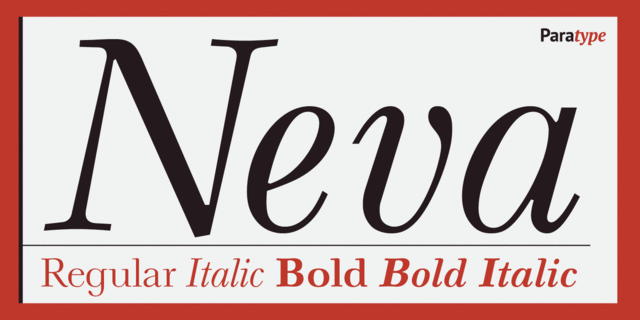
Гарнитура Нева в 2-х начертаниях для строкотливного и крупнокегельного набора была разработана в 1970 году в Отделе наборных шрифтов НПО Полиграфмаш художником книги Павлом Кузаняном (1901-1992). Шрифт создан на основе простых, строгих форм русской шрифтовой классики. На международном конкурсе имени Гутенберга в 1971 году шрифт Нева был отмечен почетным дипломом. Предназначен для набора художественной литературы и изданий по искусству, а также для акциденции. Цифровая версия и жирные начертания созданы для фирмы ParaType в 2002 году (дизайнер Любовь Кузнецова).
Ассоциации c семейством NevaКачества и характер:
благородный, консервативный, традиционный, классический, повествовательный, художественный, серебристый, образованный, острый, мастерский, точный, аристократичный, элитный, правильный, статичный, комильфо, пафосный, исторический, гуманитарный, серебрянный, осенний, вежливый, изящный, манерный, красивый, аккуратный, уважительный, прилежный, тактичный, лирический, гордый